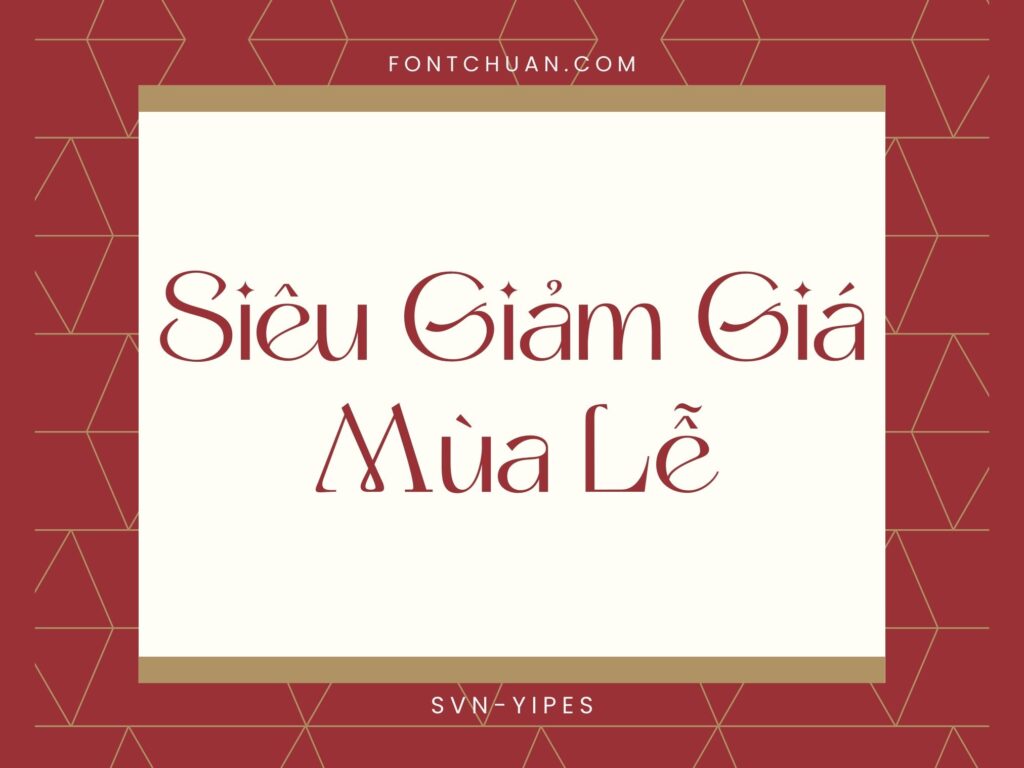
Font SVN Yipes Việt Hóa
Font SVN-Yipes là phiên bản Việt hóa của kiểu chữ Yipes, được thực hiện bởi STYLEno.1 Fonts. Yipes thuộc nhóm Font Decorative, là một kiểu chữ hiển thị (display) kết hợp giữa sự thanh lịch cổ điển và hiện đại, phù hợp cho việc tạo thiệp mời đám cưới, bố cục tạp chí, thiết kế logo, mẫu PowerPoint, trích dẫn hoặc bất kỳ đồ họa nào yêu cầu một cái nhìn bóng bẩy với nét cổ điển. Font này bao gồm các chữ cái in hoa, in thường, chữ số và ký tự đặc biệt, hỗ trợ đa ngôn ngữ.
SVN-Yipes lý tưởng cho các dự án thiết kế yêu cầu sự sang trọng và độc đáo, như thiệp mời, logo, tiêu đề và các ấn phẩm truyền thông. Các ngành nghề như thiệp cưới, quảng cáo và ẩm thực có thể tận dụng font này để tạo điểm nhấn trong thiết kế. Ngoài ra, font cũng thích hợp cho các sự kiện như Tết, Giáng sinh, Valentine và các lễ hội khác.